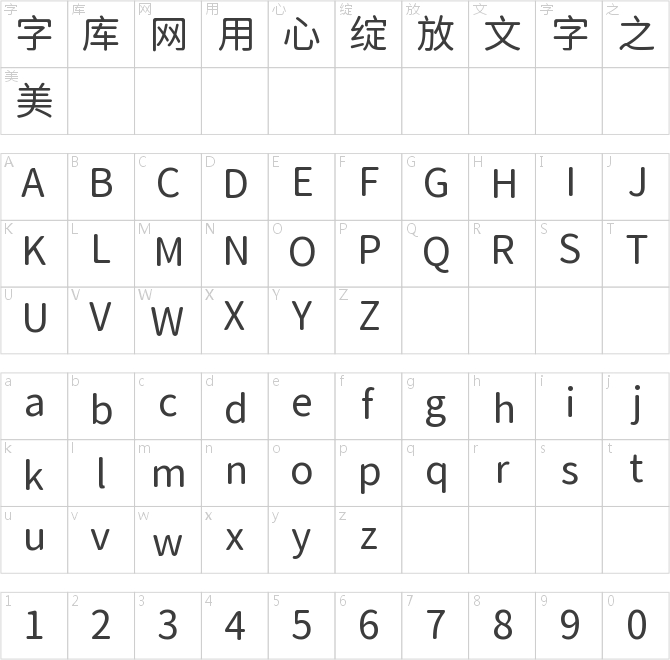
字体名称: 狮尾圆体
狮尾圆体基于思源黑体的拔脚和加圆改造,是一款更加简明现代化的字体。台湾的Max之前随手修改了一下GOOGLE提供的思源字体,之前是完成了思源黑体的拔脚,一下子就完成了,所以发布了狮尾黑体。现在又顺便挑战一下把黑体变成圆体,就有了现在这款狮尾圆体。支持简体中文、繁体中文、韩文与日文。和思源黑体一样,狮尾圆体支持7种的字重。
狮尾圆体字体SweiGothicCJKtc狮尾圆体七字重打包字库是一款让人赏心悦目、百看不厌的字体打包,适合各类广告和产品包装设计应用,字体大小22.2MB,格式为ttf字体,上传用户是Pt.赵鹏涛,作者/版权方为max-everyday.com